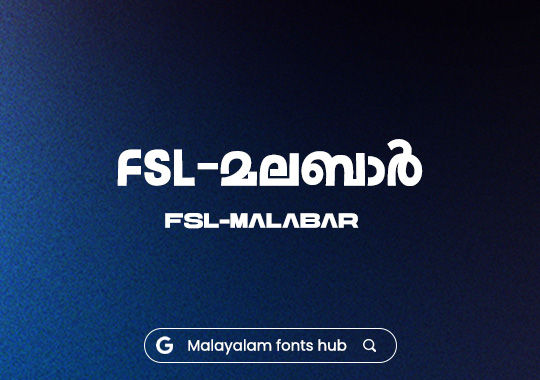
FSL-Malabar | Modern Bilingual Variable Font for Malayalam & English
മലയാളവും ഇംഗ്ലീഷും ഒരുപോലെ ഉപയോഗിക്കേണ്ടി വരുന്ന New Gen ഡിസൈനുകൾക്കായി രൂപകൽപ്പന ചെയ്ത ഒരു ബൈലിംഗൽ വേരിയബിൾ ഫോണ്ടാണ് (Bilingual Variable Font) FSL-Malabar. രണ്ട് ഭാഷകളിലെയും അക്ഷരങ്ങൾ തമ്മിൽ കൃത്യമായ ബാലൻസ് നിലനിർത്തുന്നു എന്നതാണ് ഈ ഫോണ്ടിന്റെ ഒരു പ്രത്യേകത. ഡിജിറ്റൽ ഇന്റർഫേസുകൾ മുതൽ പ്രിന്റ് മീഡിയ വരെ ഒരേപോലെ ഉപയോഗിക്കാൻ സാധിക്കുന്ന രീതിയിലാണ് ഇതിന്റെ നിർമ്മാണം.
പ്രത്യേകതകൾ:
Dynamic Weight Flexibility: വേരിയബിൾ ഫോണ്ട് സാങ്കേതികവിദ്യ ഉപയോഗിക്കുന്നതിനാൽ, അക്ഷരങ്ങളുടെ Weight ആവശ്യാനുസരണം കൃത്യമായി ക്രമീകരിക്കാൻ സാധിക്കും.
Seamless Visual Balance: മലയാളം, ഇംഗ്ലീഷ് സ്ക്രിപ്റ്റുകൾ ഒരുമിച്ച് ടൈപ്പ് ചെയുമ്പോൾ അവ തമ്മിലുള്ള Proportions വളരെ കൃത്യമായിരിക്കാൻ FSL-Malabar സഹായിക്കുന്നു.
High Readability: എല്ലാ തരം സ്ക്രീനുകളിലും പ്രിന്റിംഗിലും അക്ഷരങ്ങൾ വളരെ വ്യക്തമായി വായിക്കാൻ സാധിക്കുന്ന രീതിയിലുള്ള ഡിസൈൻ.
Versatile Use Case: വെബ്സൈറ്റുകൾ (UI/UX), മാസികകൾ (Editorial Layouts), ബ്രാൻഡിംഗ് എന്നിവയ്ക്ക് ഏറ്റവും അനുയോജ്യം.
നിങ്ങളുടെ പ്രോജക്റ്റുകളിൽ പുതിയൊരു ട്രെൻഡിങ് കൊണ്ടുവരാൻ FSL-Malabar മികച്ചൊരു ഓപ്ഷനാണ്.